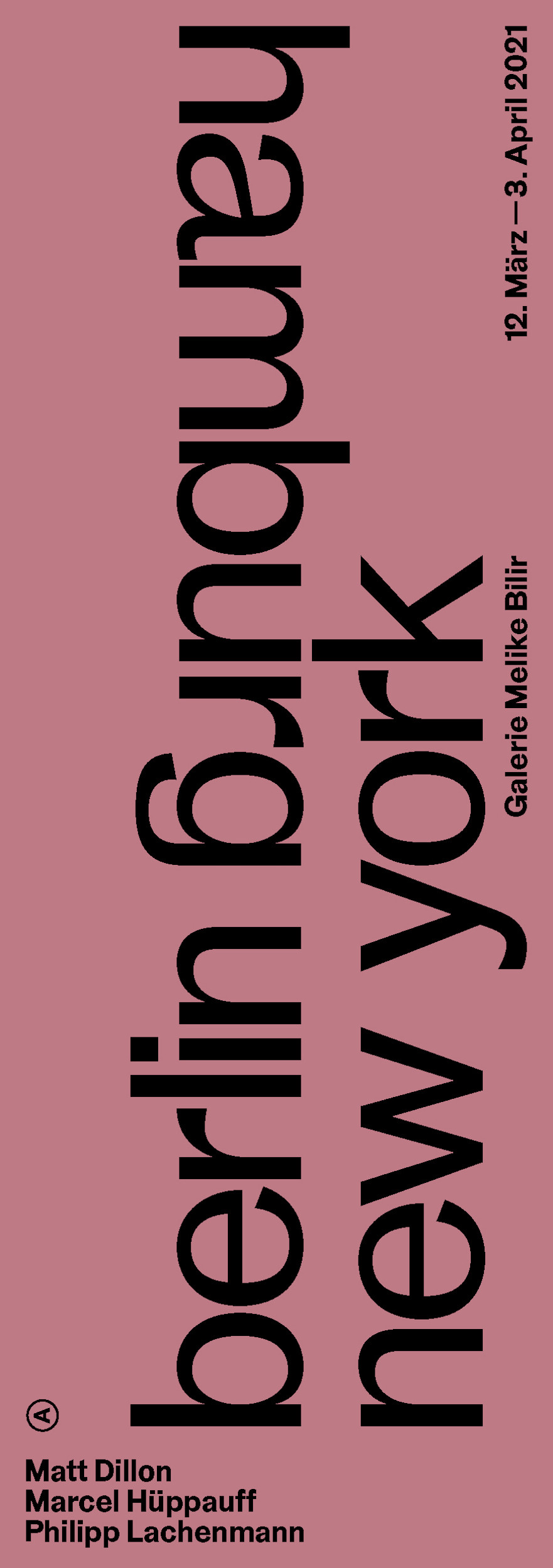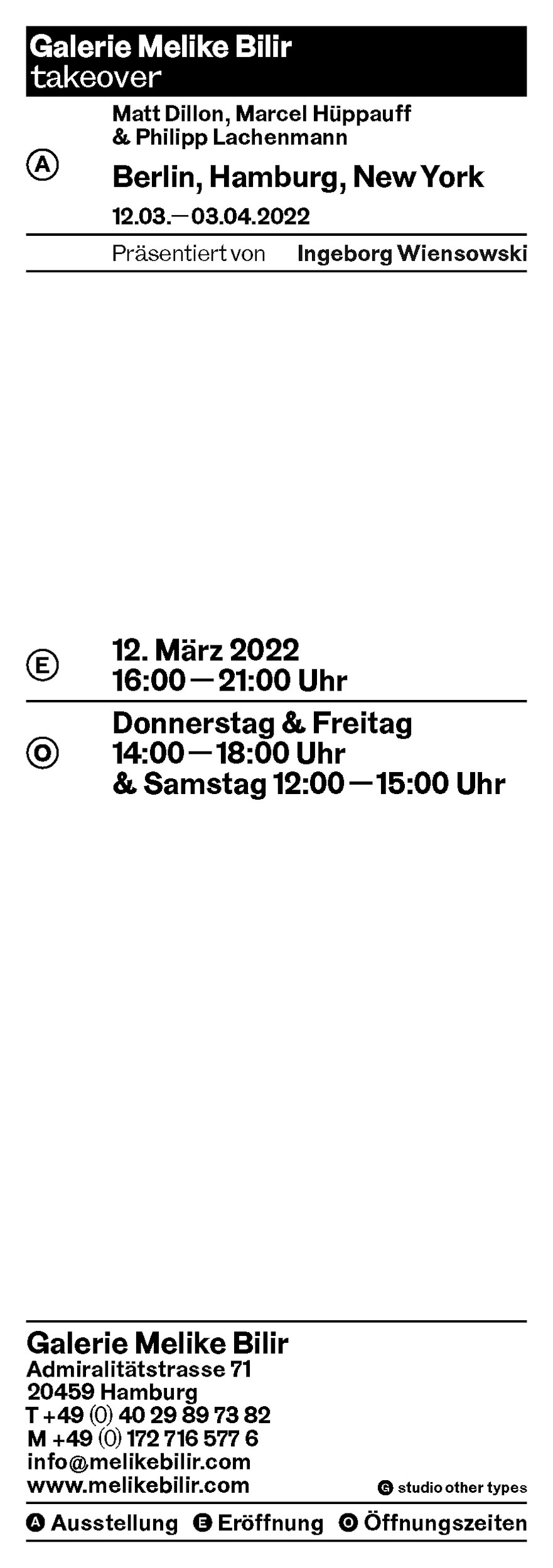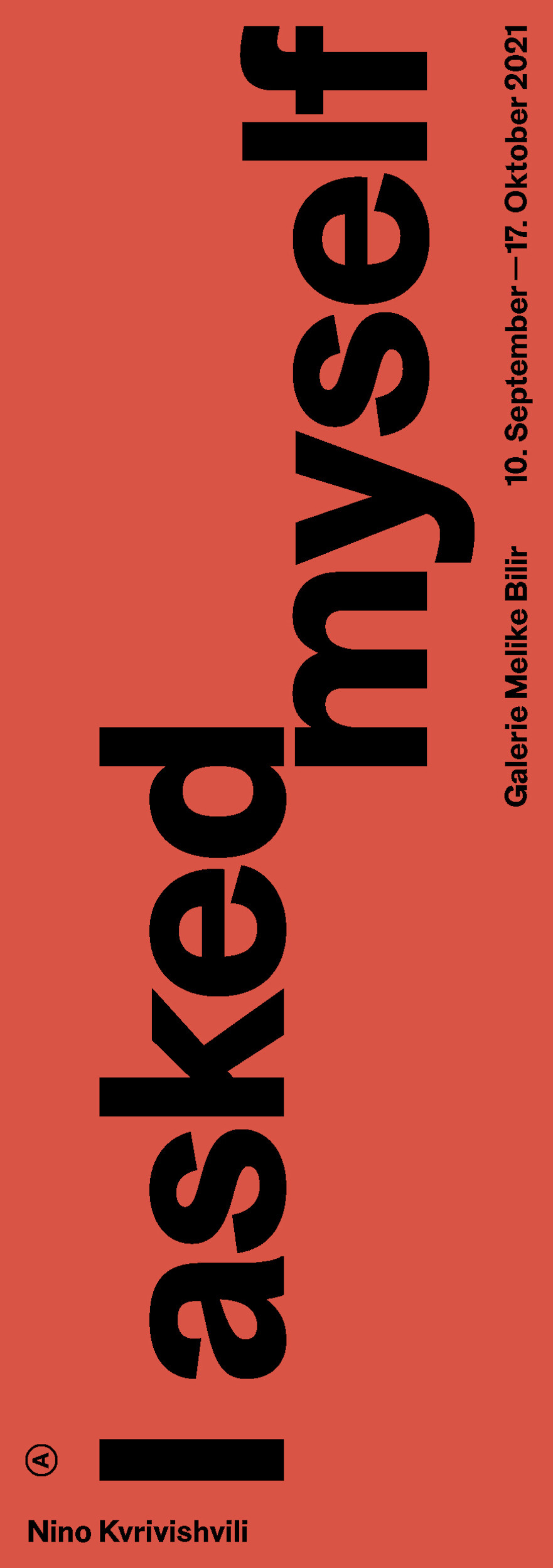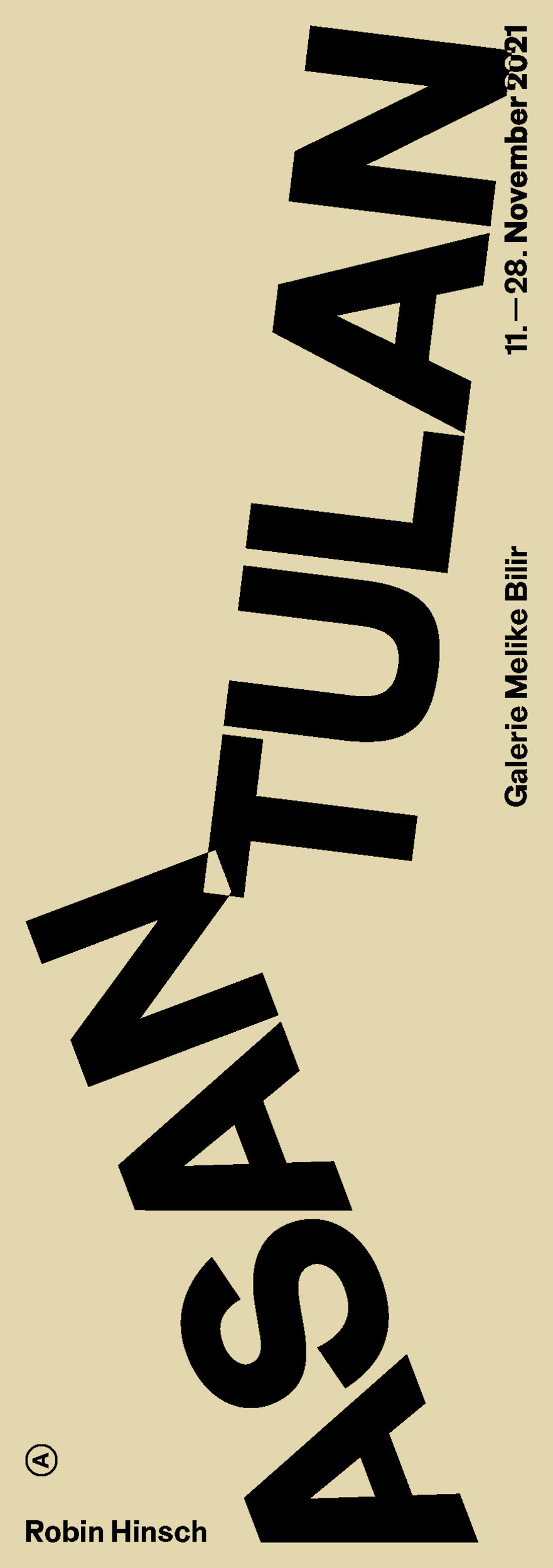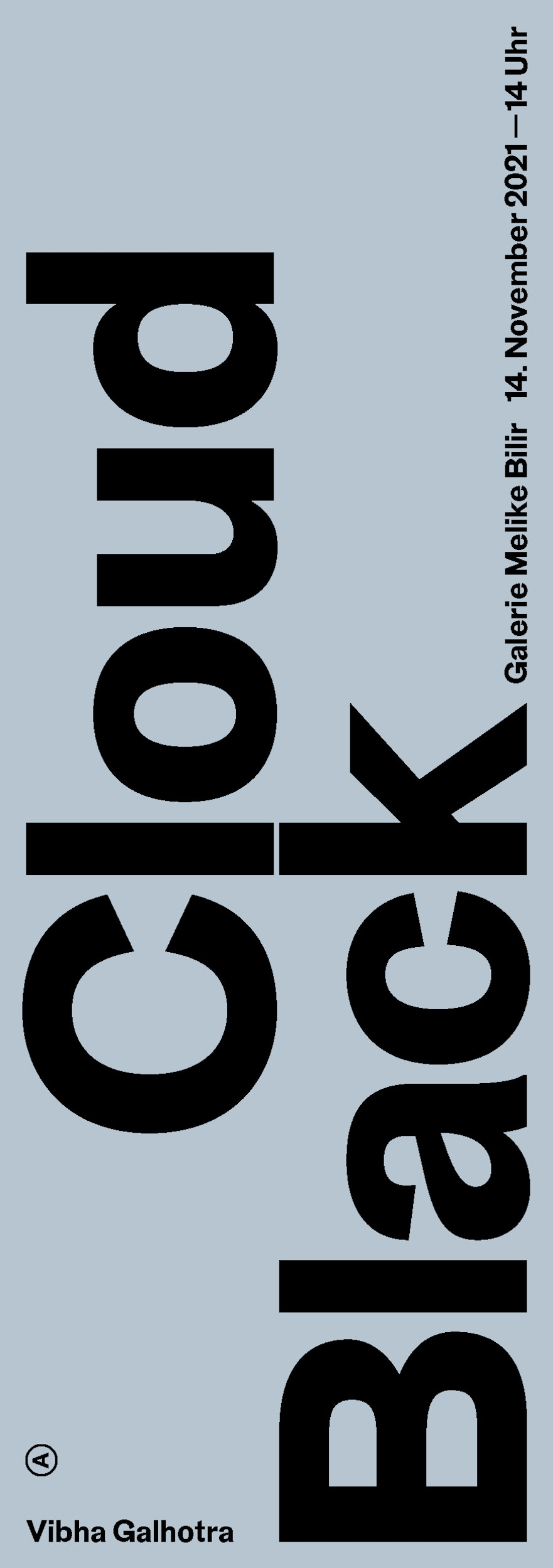
Ausstellungsflyer 2021
Eine Übersicht der Flyer, die für die verschiedenen Ausstellungen in der Galerie Melike Bilir im Jahr 2021 entstanden sind. Die Flyer zeichnen sich durch einen spielerischen Umgang mit Schrift aus und bleiben stets im Rahmen der Corporate Identity der Galerie.
Schrift: BT Grotesk von Scott Vander Zee